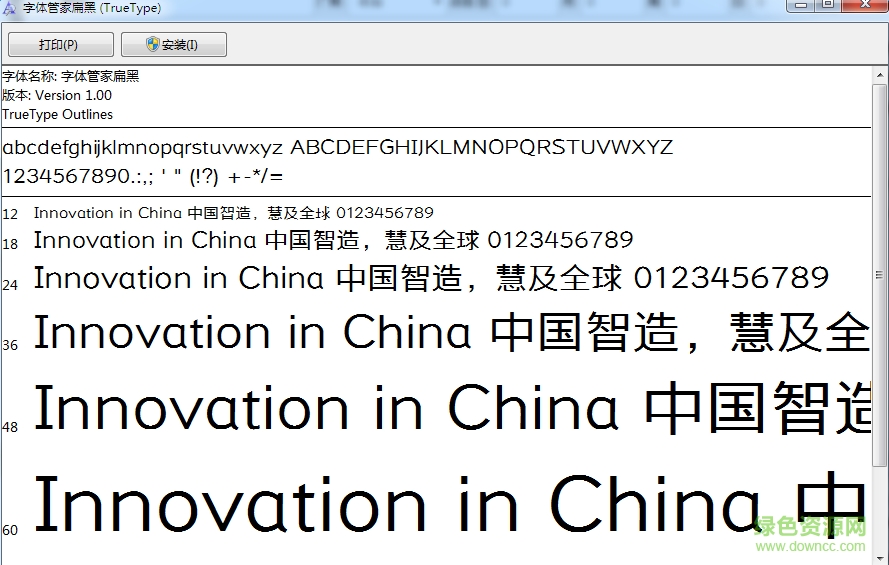
字體管家扁黑體是一款更具黑體字體演變而來的獨特的電腦字體,在保留了黑體字粗壯有力,醒目美觀的特點同時,將字體變得扁平的一些,看上去更加的具有特色,感興趣的朋友可以來綠色資源網(wǎng)下載!
字體管家扁黑體是一款黑體中文簡體漢字,該字體字體較常用的黑體略扁,字形端正易讀,又十分工整簡潔,可以應(yīng)用于廣告設(shè)計、名片設(shè)計、包裝印刷、產(chǎn)品設(shè)計等應(yīng)用。